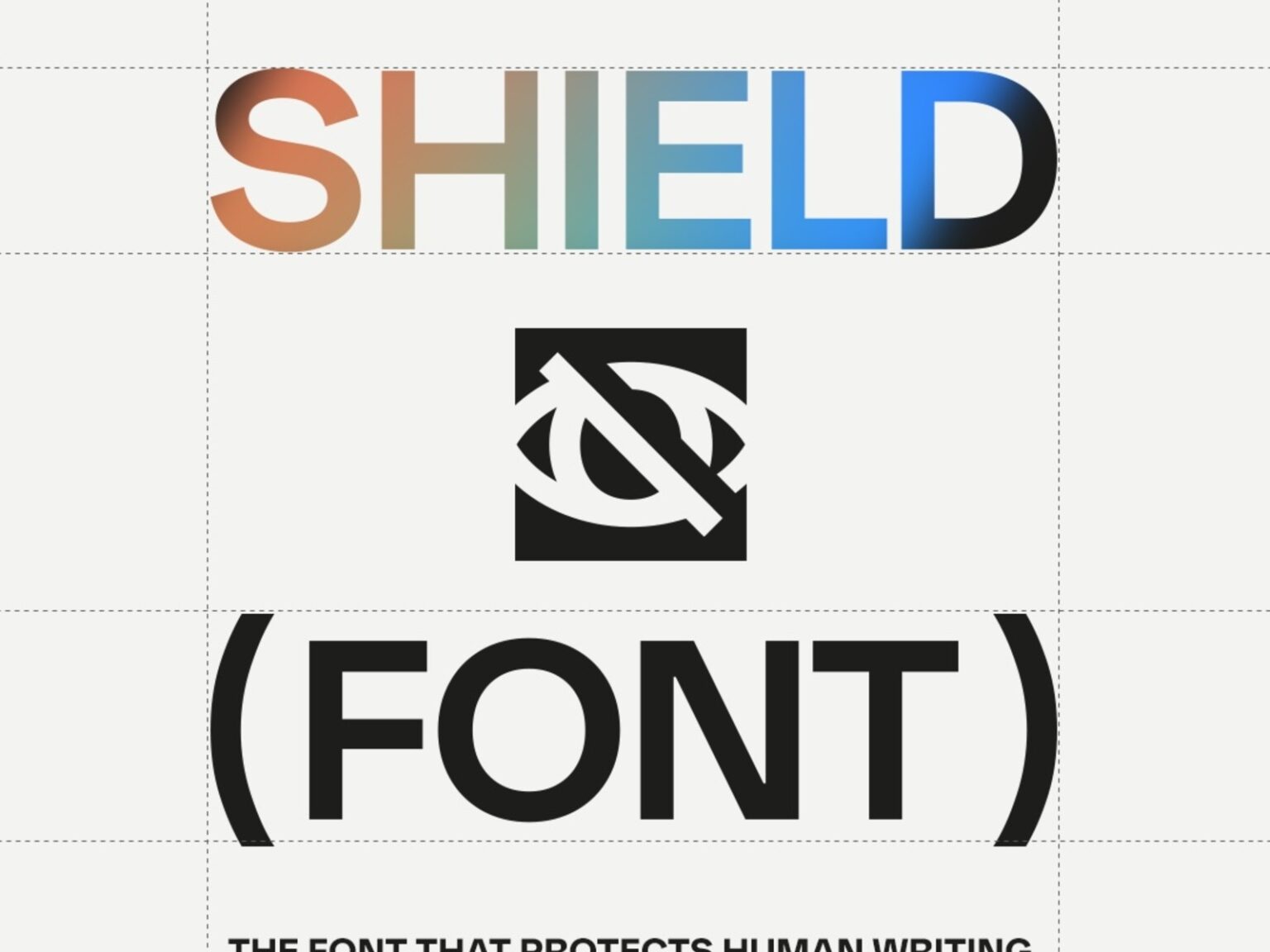
쉴드폰트, AI 스크래핑에 맞서는 서체
덴마크의 서체 파운드리 Playtype가 크리에이티브 스튜디오 S&A(Seneda & Abrucio)와 협업해 AI 스크래핑으로부터 온라인 콘텐츠를 보호하기 위한 오픈소스 서체 ‘ShieldFont’를 공개했습니다. 프로젝트는 AI 자체를 반대하기보다, 인터넷에 공개된 모든 콘텐츠를 AI 학습 데이터로 자유롭게 활용할 수 있다는 관행에 문제를 제기하는 데 초점을 맞췄습니다.
ShieldFont는 Playtype의 기존 서체 ‘Optik’을 기반으로 타입 디자이너 Jeppe Pendrup이 개발했습니다. 사용자가 화면에서 보는 텍스트는 일반적인 서체와 동일하게 보이지만, HTML 소스 코드에서는 일부 단어를 다른 문자열로 치환하는 방식으로 동작합니다. 사람은 정상적인 문장을 읽을 수 있지만, 웹페이지를 수집하는 AI 크롤러는 변형된 텍스트를 가져가게 되어 학습 데이터의 품질을 떨어뜨립니다. 이는 시각적 표현과 기계가 수집하는 데이터를 분리해 콘텐츠를 보호하는 새로운 접근 방식입니다.
프로젝트는 AI 모델의 학습을 원천적으로 차단하기보다 대규모 무단 스크래핑의 비용과 복잡성을 높이는 데 목적이 있습니다. 콘텐츠 제작자는 별도의 워터마크나 접근 제한 없이 기존 웹페이지에 ShieldFont를 적용해 자신의 글을 보호할 수 있으며, 프로젝트는 누구나 사용할 수 있도록 오픈소스로 공개됐습니다. AI 시대에 서체가 단순한 읽기 도구를 넘어 디지털 권리 보호를 위한 기술적 인터페이스로 활용될 수 있다는 점에서 주목받고 있습니다.